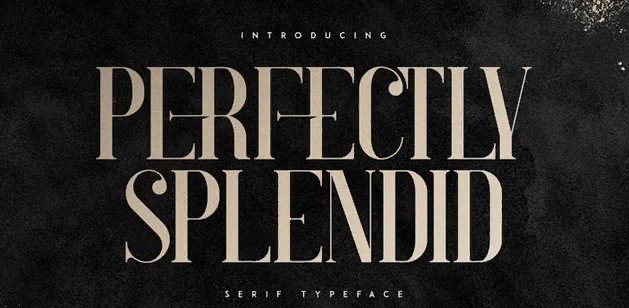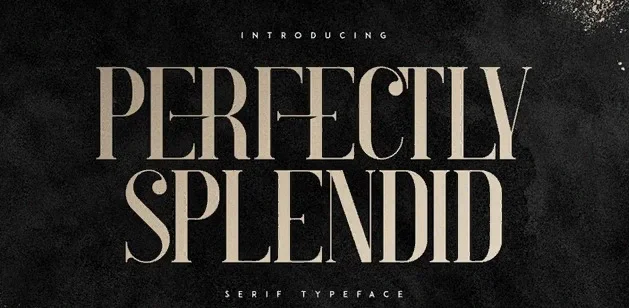
Представляем вашему вниманию шрифт Perfectly Splendid с засечками!
Perfectly Splendid - это волшебный, изысканный шрифт с 5 весами, который очарует ваш следующий проект. Очень универсальный шрифт, который отлично работает в больших и малых размерах. Поддерживаются основные латинские и расширенные латинские наборы символов!
Perfectly Splendid идеально подходит для брендинговых проектов, дизайна домашней утвари, упаковки товаров, заголовков журналов - или просто как стильное наложение текста на любое фоновое изображение.
Прописные цифры, пунктуация и символы
Штриховой, светлый, обычный, полужирный, черный
Лигатуры
Многоязычная поддержка